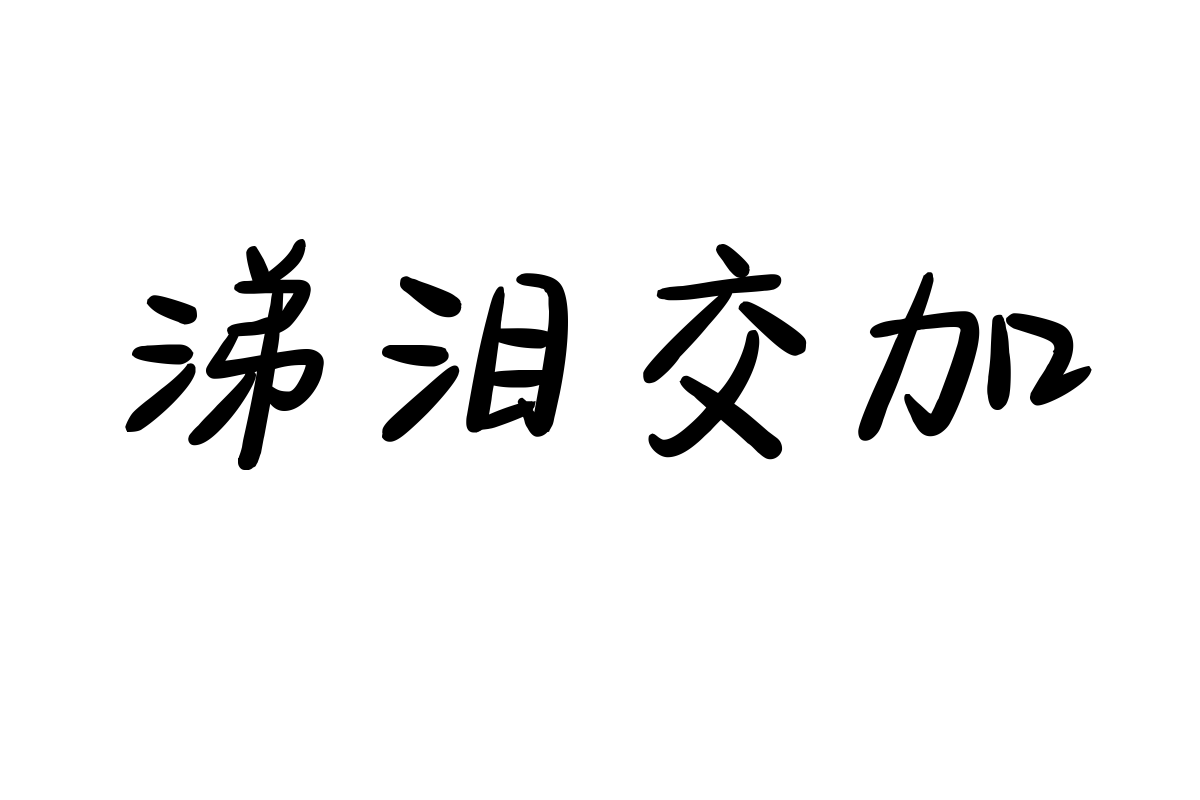
也字工厂蜡笔体是一款具有独特风格的中文字体,它采用了简洁的线条和形状,给人一种轻松愉快的感觉。这种字体适合用于儿童书籍、教育材料、广告宣传等场合,能够吸引人们的注意力并传达出积极的信息。
也字工厂蜡笔体的笔画粗细适中,线条流畅,给人一种轻盈的感觉。它的字形结构紧凑,没有过多的装饰元素,使得整个字体看起来更加简洁明了。此外,这种字体还具有一定的可读性,适用于各种文字排版。
总的来说,也字工厂蜡笔体是一款非常适合儿童和教育机构使用的字体。它不仅能够提升文本的视觉效果,还能够传递出积极向上的信息,让人们在阅读过程中感受到快乐和愉悦。